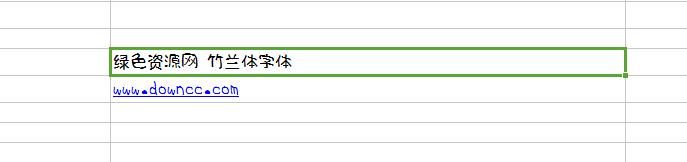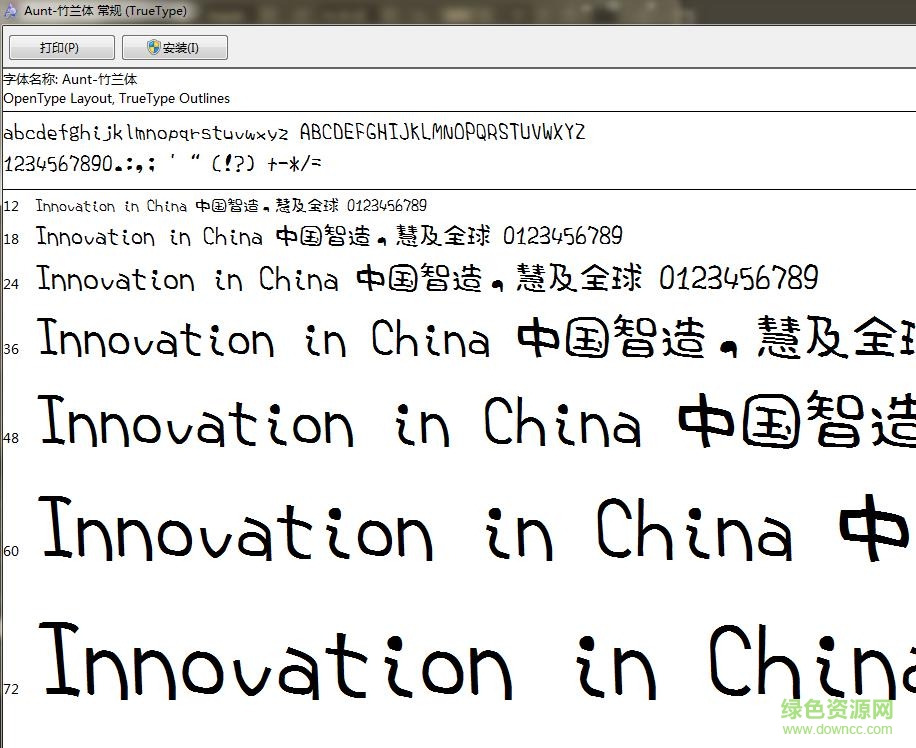
aunt竹蘭體字體
竹蘭體ttf該字體擁有十分精美的視覺效果,是aunt字體中的一款十分不錯(cuò)的字體樣式,這款字體的每一個(gè)結(jié)構(gòu)都十分圓潤,同時(shí)在各類媒體制作,廣告制作中能夠帶來不錯(cuò)的效果!
竹蘭體ttf小編點(diǎn)評(píng)
多種樣式的字體風(fēng)格,讓你能夠隨心的感受最佳的字體顯示效果,支持用戶將此字體運(yùn)用到各行各業(yè)中,十分不錯(cuò)!
竹蘭體
竹蘭體字體介紹